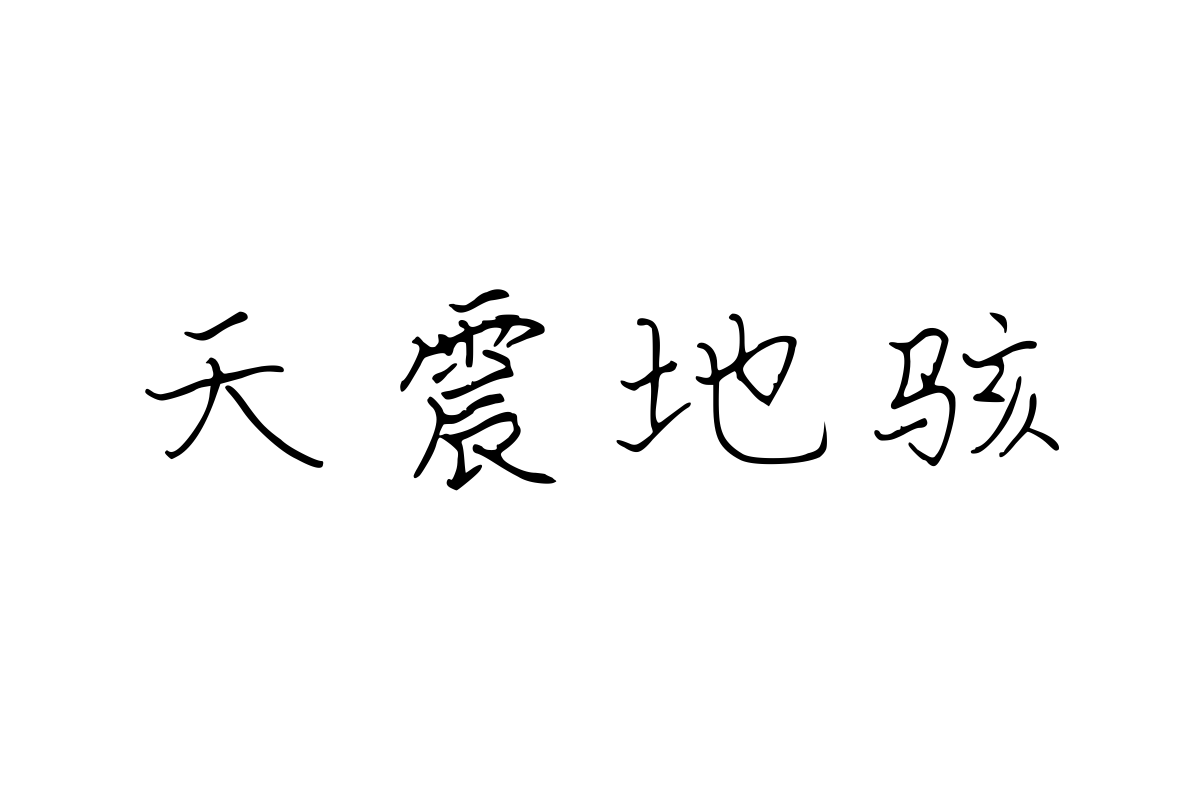
汉呈谭发社硬笔楷书是一套专为汉字书写设计的字体。它的特点是笔画清晰,结构严谨,字形规整,易于书写和识别。这套字体适合用于各种正式的书面材料,如公文、报告、信件等。
汉呈谭发社硬笔楷书的特点如下:
1. 笔画清晰:每个字的笔画都写得非常清晰,没有模糊不清的部分。这使得阅读者能够轻松地理解每个字的含义。
2. 结构严谨:每个字的结构都非常严谨,没有多余的笔画或结构。这使得整个字体看起来非常整洁和有序。
3. 字形规整:每个字的字形都保持规整,没有过于夸张或过于简单的情况。这使得整个字体看起来非常美观和大方。
4. 易于书写:由于每个字的笔画都写得非常清晰,使得书写者能够轻松地完成每一个字的书写。这为书写提供了极大的便利。
5. 适用于多种场合:这套字体不仅适用于日常书写,也非常适合用于正式的书面材料,如公文、报告、信件等。这使得它在各种场合下都能发挥出最大的效用。